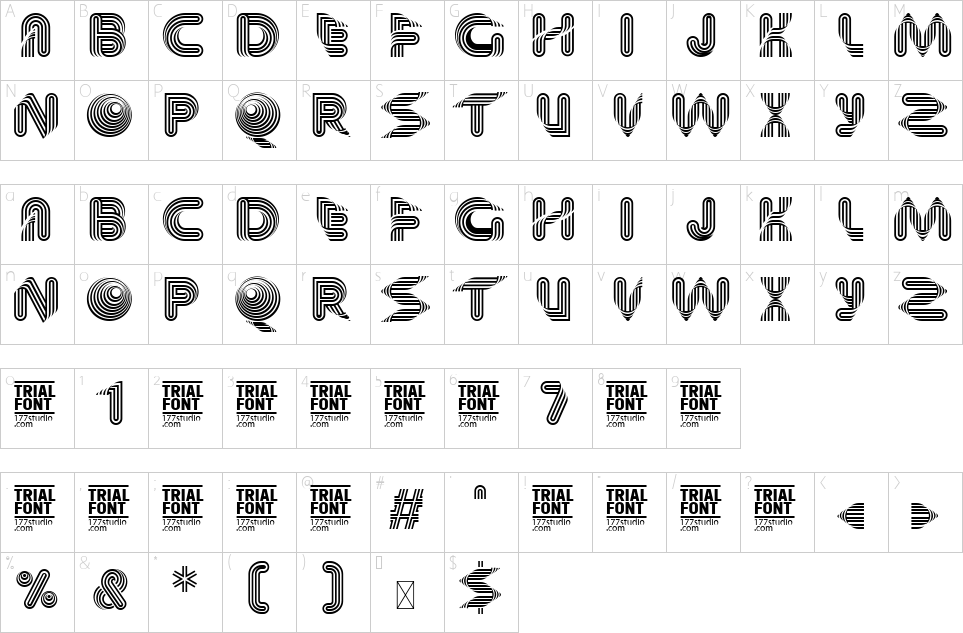
Descubra a elegância da Goline Font no seu próximo projeto criativo! Desenvolvida pela 177studio.com, esta fantástica fonte ganhou a aprovação de muitos designers ao redor do mundo com sua gradação suave e personalidade única. Com uma variedade rica de estilos e tamanhos, Goline é perfeita para criar texturas sofisticadas em sites ou aplicativos. Adquira sua cópia hoje e experimente a tranquilidade que essa font oferece ao seu design! Disponível tanto para Windows quanto Mac, você pode personalizar sua interface de escritório e criar ambientes digitais envolventes. Tente Goline agora e veja como ela pode revolucionar seus projetos.